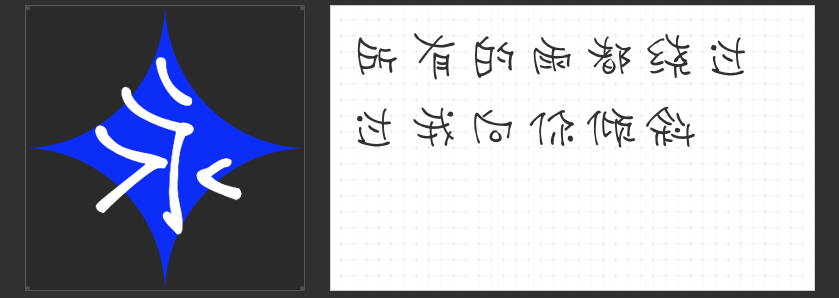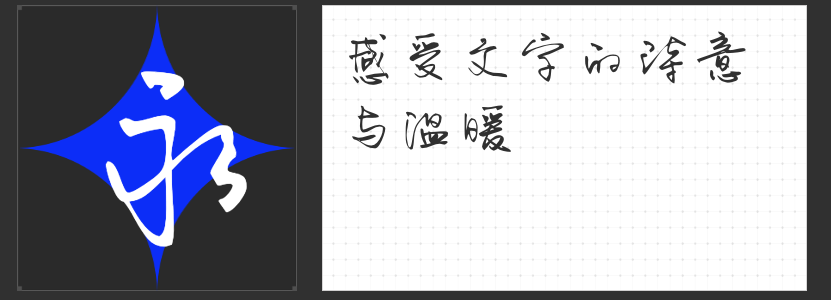
清新雅致:“小豆岛”手写体的魅力与应用
在快节奏的现代生活中,人们越来越渴望回归自然、寻找心灵的宁静。“小豆岛”系列字体正是这样一组能够触动人心、带来温馨感受的手写体集合。该系列字体以其独特的风格和丰富的表现力,在众多字体中脱颖而出,成为设计师们青睐的选择。本文将详细介绍四款“小豆岛”系列手写字体,探讨它们的特点及在设计中的应用。
1. 小豆岛默陌乐童简
“小豆岛默陌乐童简”是一款充满童真与活力的手写体。它的笔画圆润流畅,结构轻松自然,仿佛孩童纯真的笔迹,给人一种温暖而亲切的感觉。这款字体非常适合用于儿童读物、教育类产品、亲子活动宣传等场合。它可以有效地拉近与目标受众的距离,营造出温馨、友好的氛围。
2. 小豆岛默陌纸鸢草书简
“小豆岛默陌纸鸢草书简”则展现了一种更加自由奔放的风格。它以草书为基础,笔触连绵不断,如同风筝在空中自由翱翔。字体中蕴含着浓厚的艺术气息,适合用于艺术展览、文化创意产品的设计以及个人博客、社交媒体上的标题和签名等。这款字体能够为作品增添一抹独特的艺术魅力,吸引读者的目光。
3. 小豆岛惠中谐趣简繁
“小豆岛惠中谐趣简繁”是一款既简洁又不失趣味性的手写体。它在保证字体清晰可读的同时,加入了一些巧妙的设计元素,使得每个字母都显得生动有趣。这款字体适用于各种商业广告、海报设计、包装设计等场景。无论是在线上还是线下,它都能迅速抓住人们的注意力,传递出轻松愉快的信息。
4. 小豆岛默陌枝桠简
最后介绍的是“小豆岛默陌枝桠简”。这款字体以树枝为灵感来源,笔画之间错落有致,仿佛自然界中的枝桠般自然生长。它不仅保留了手写体的温暖感觉,还带有一丝神秘的自然之美。适用于自然风光摄影集、环保主题宣传资料、植物园导览图等设计项目。通过使用这款字体,可以有效地增强作品与自然环境之间的联系,激发人们对大自然的热爱之情。
总之,“小豆岛”系列字体以其清新雅致的风格和丰富多样的应用场景,成为了许多设计师的理想选择。无论是想要为作品注入一丝童趣,还是希望传达出自然和谐的信息,都可以在这组字体中找到合适的答案。希望本文的介绍能够帮助您更好地理解和运用这些美丽的手写体,创造出更多令人难忘的设计作品。